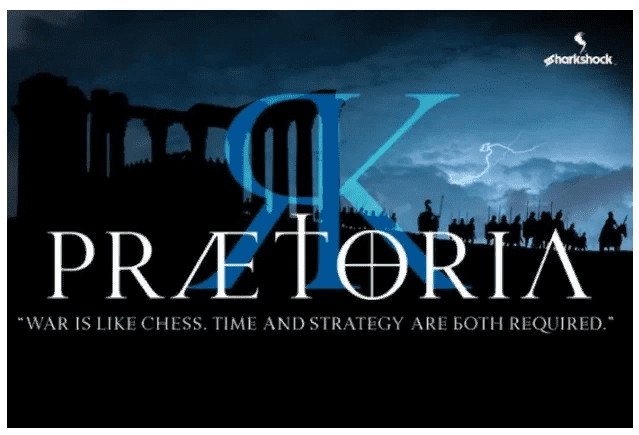
Praetoria - это шрифт с засечками, который был создан по образцу римских квадратных капителей, использовавшихся в Древнем Риме. Некоторые строчные буквы являются вымышленными вариациями своих прописных аналогов. Однако некоторые из них, такие как б и м, были взяты из русского и греческого алфавитов соответственно.
Этот шрифт предназначен для игр, постеров фильмов и обложек книг. Вы можете использовать исключительно прописные буквы, но крайне не рекомендуется делать то же самое со строчными. Рекомендуется просто использовать их в качестве дополнения к прописным.
Praetoria - это шрифт с засечками, который был создан по образцу римских квадратных капителей, использовавшихся в Древнем Риме. Некоторые строчные буквы являются вымышленными вариациями своих прописных аналогов. Однако некоторые из них, такие как б и м, были взяты из русского и греческого алфавитов соответственно.
Этот шрифт предназначен для игр, постеров фильмов и обложек книг. Вы можете использовать исключительно прописные буквы, но крайне не рекомендуется делать то же самое со строчными. Рекомендуется просто использовать их в качестве дополнения к прописным.